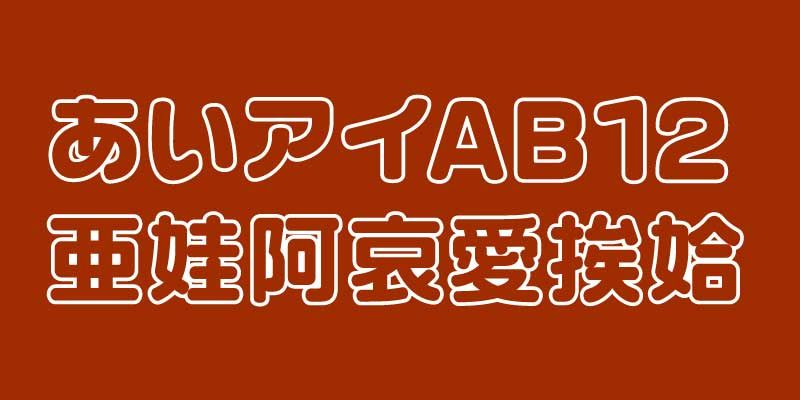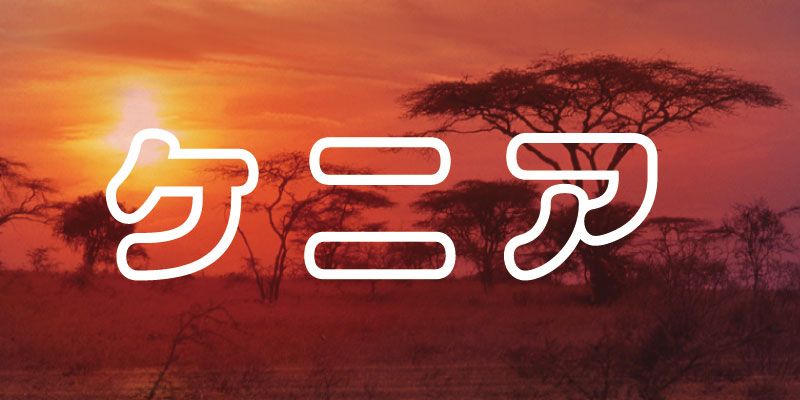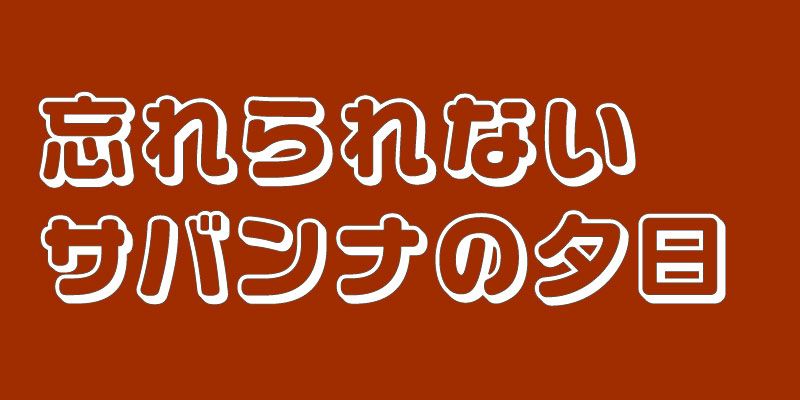
VDL-LogoMaru-pop은 VDL-LogoMaru의 디자인을 기반으로 하는 장식적인 서체 패밀리입니다. 글리프 윤곽선이 강조된 VDL-LogoMaru-pop-FutoLine과 윤곽선이 음영 처리되어 3차원 효과를 주는 VDL-LogoMaru-pop-Shadow로 구성되어 있습니다.
디스플레이용 글꼴인 이 글꼴은 9,354개의 글리프(Adobe-Japan1-3 문자 컬렉션 기반)를 포함합니다.
편집 작업, 팝 디스플레이 디자인과 더불어 이미지 및 비디오 콘텐츠 등 넓은 용도로 이 서체를 사용하여 눈길을 사로잡는 효과 및 시각적 효과와 함께 타이포그래피 표현을 연출할 수 있습니다.